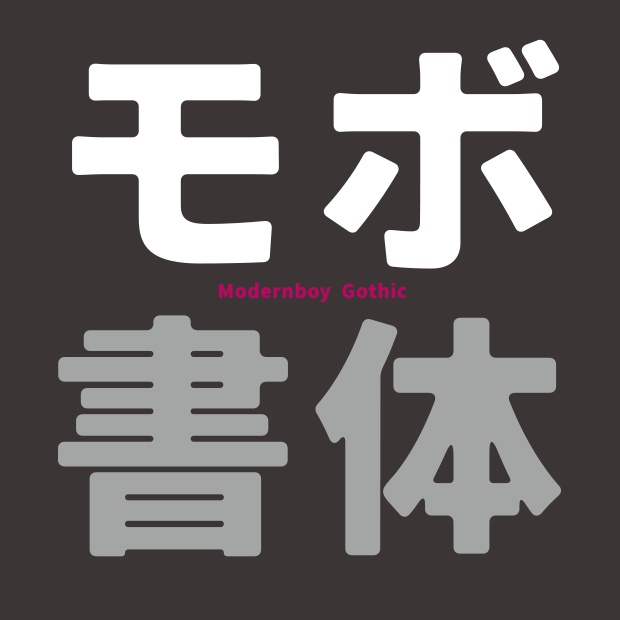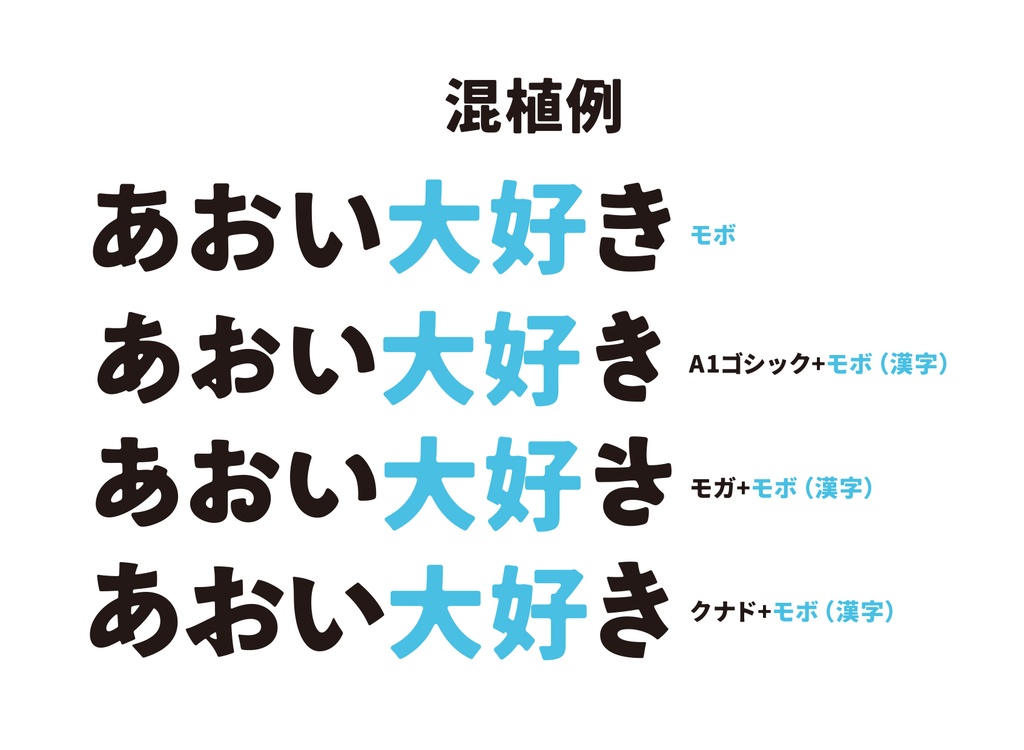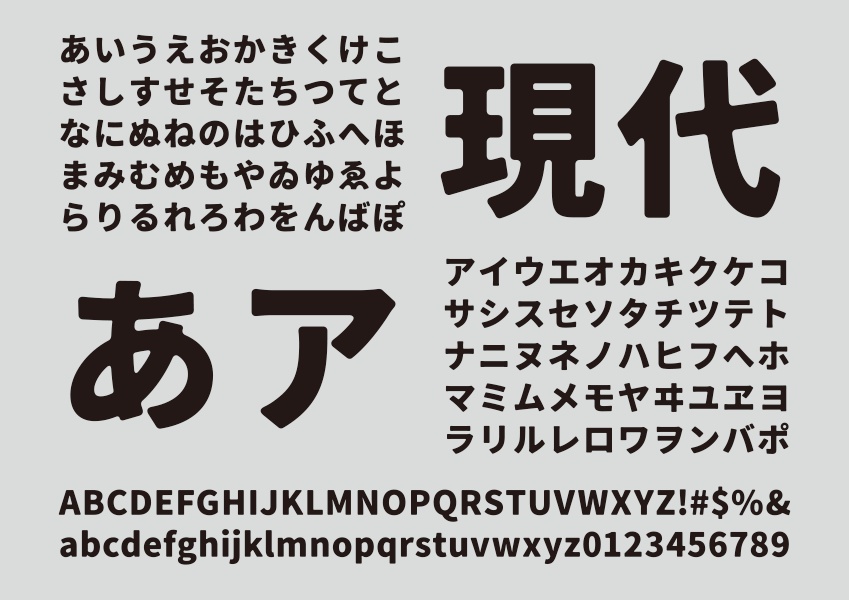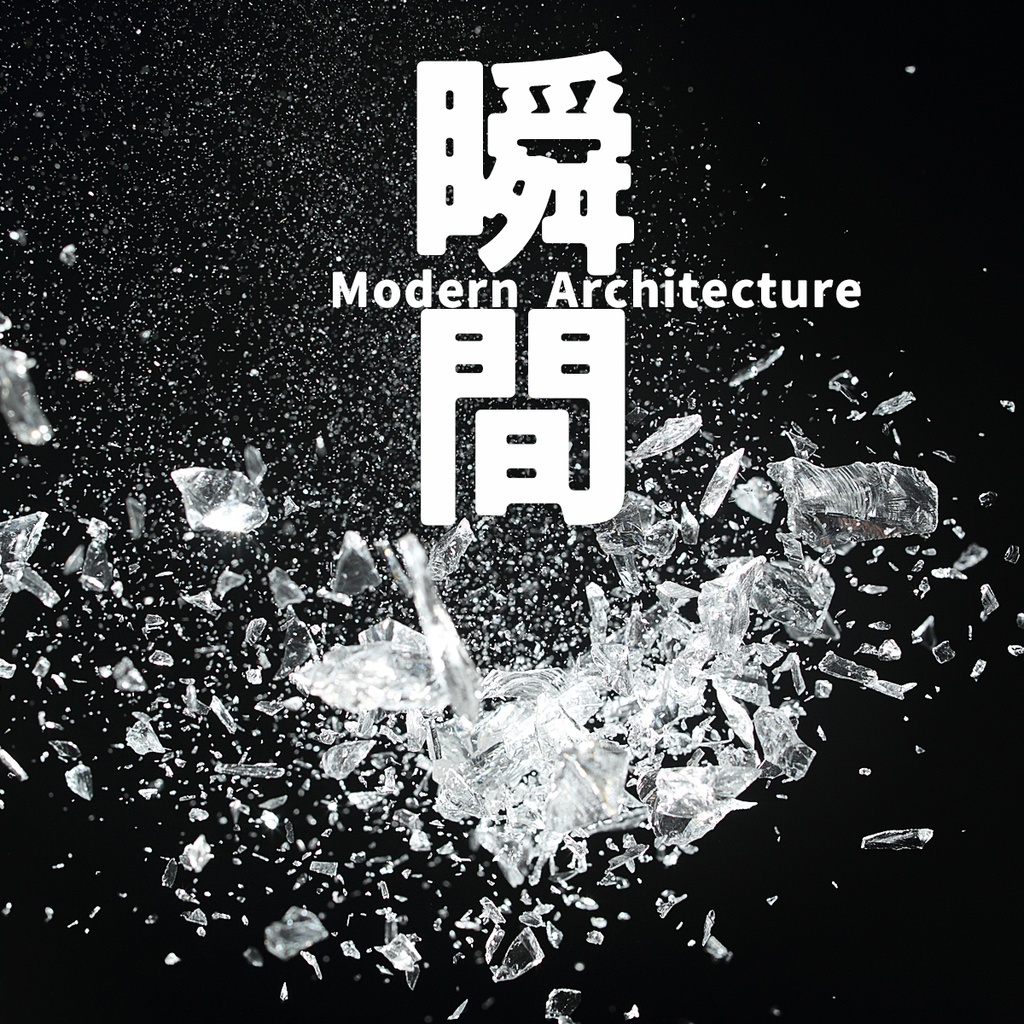
时髦公子黑是一种具有柔和复古感的字体,通过在带有现代骨架的哥特式边角上添加圆角。 超过 8000 个字符,您可以放心使用。
我们收到了与流行的 Moga 字体 (https://flopdesign.booth.pm/items/1817411) 匹配的免费汉字字体的请求,因此我们创建了它。
“时髦公子黑”是一款书写很新颖的字体,字体大方,适合各种设计作品使用!欢迎下载!